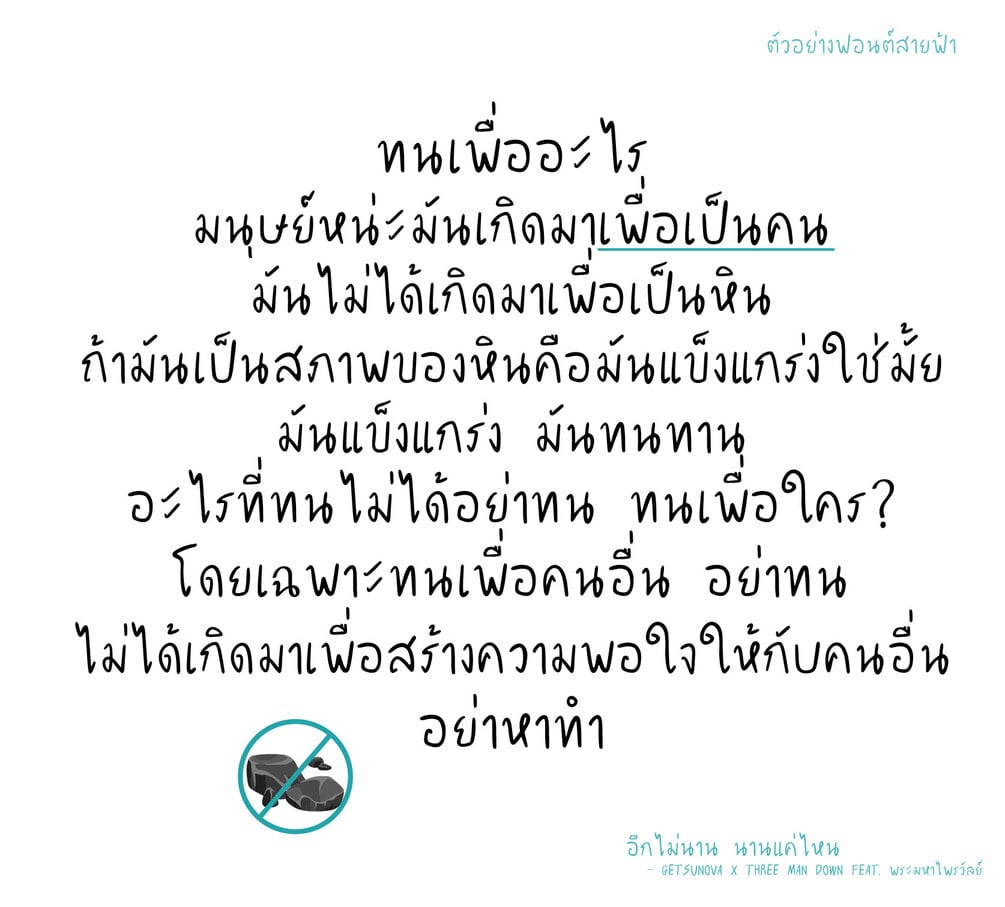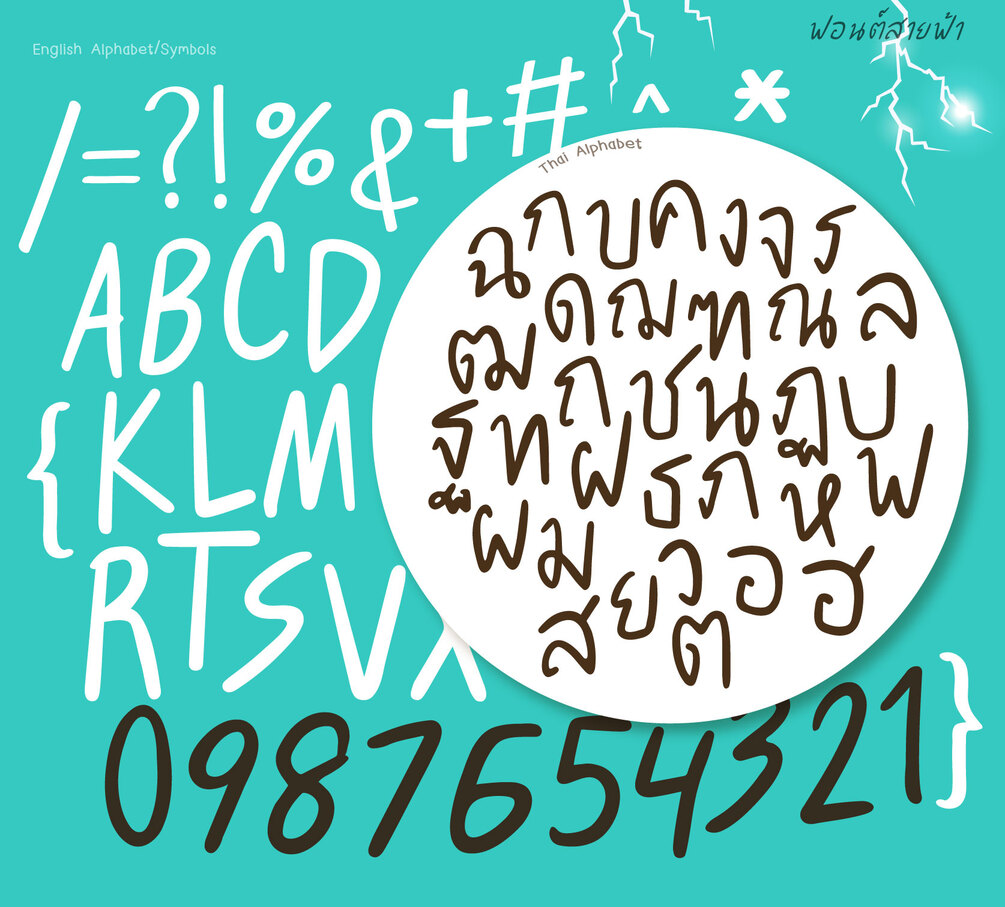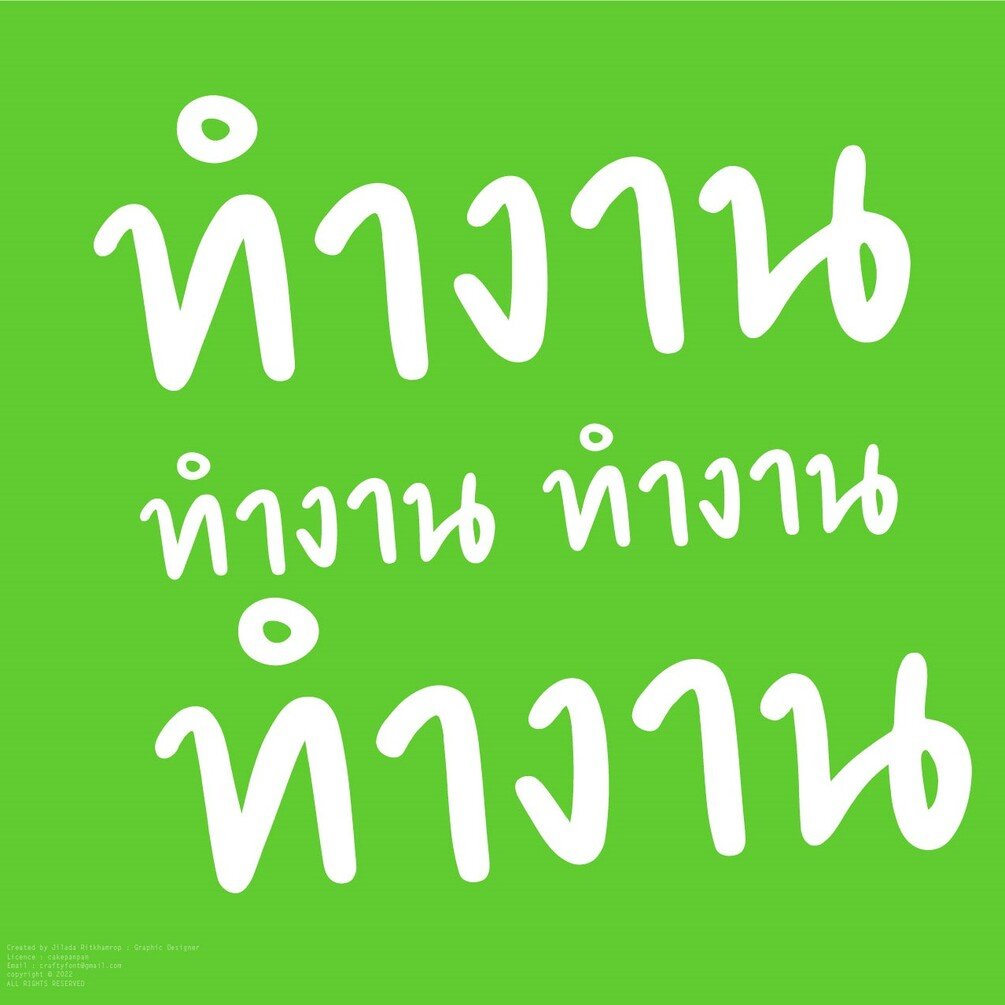
Saifah Font (ฟอนต์สายฟ้า)
เข้าหน้าฝน ขอประชาชนระวังฟ้าผ่า! 🌩️🌩️
ฟอนต์ตัวใหม่ ฟอนต์สายฟ้า เปรี้ยงๆ เขียนด้วยความโกรธ ยิ่งตัวหนา ยิ่งโกรธมาก!
แฟมิลี่ชุดนี้มีถึง 3 แบบด้วยกัน! ตัวปกติ ตัวหนา และ ตัวเอียง
ฟอนต์มีทั้งภาษาไทยและภาษาอังกฤษเลยนะคะ บวกลบคูณหารมีให้ใช้ครบ ฝากไว้ในอ้อมอกอ้อมใจพี่จ๋าด้วยนะจ๊ะ